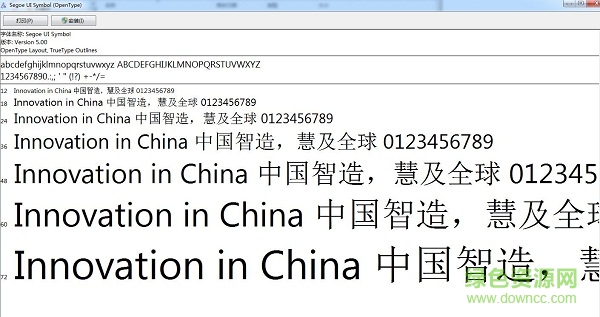
segoe ui是什么字體?segoe ui+微軟雅黑都是微軟推出的系統(tǒng)字體,字形平滑而美觀,可讀性強(qiáng),Microsoft office和Vista里面都有這款無(wú)襯線字體,有需要者歡迎免費(fèi)下載!
segoe ui字體介紹
這是微軟公司諸多新產(chǎn)品中用戶界面的字體,和Tahoma一樣仍然是一款不等寬字體。新的Segoe UI字體利用了ClearType顯示技術(shù)的優(yōu)勢(shì),比目前的系統(tǒng)字體更加現(xiàn)代化。